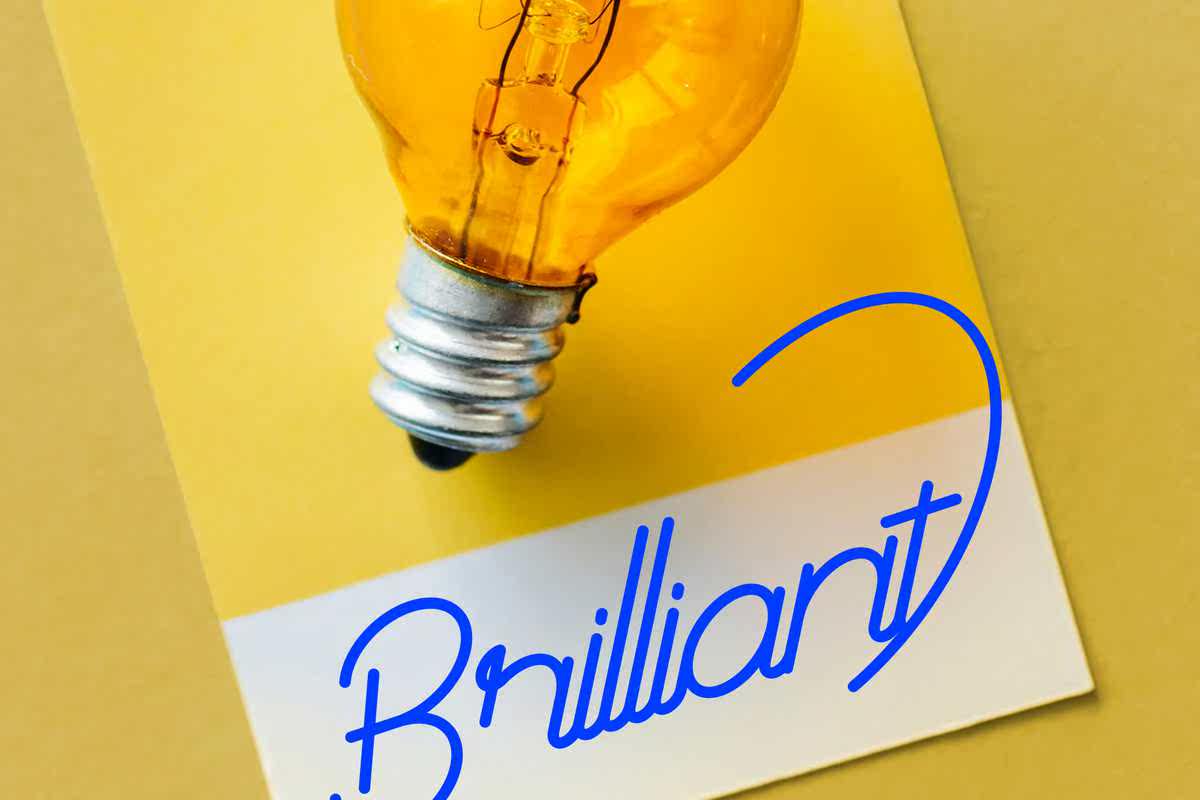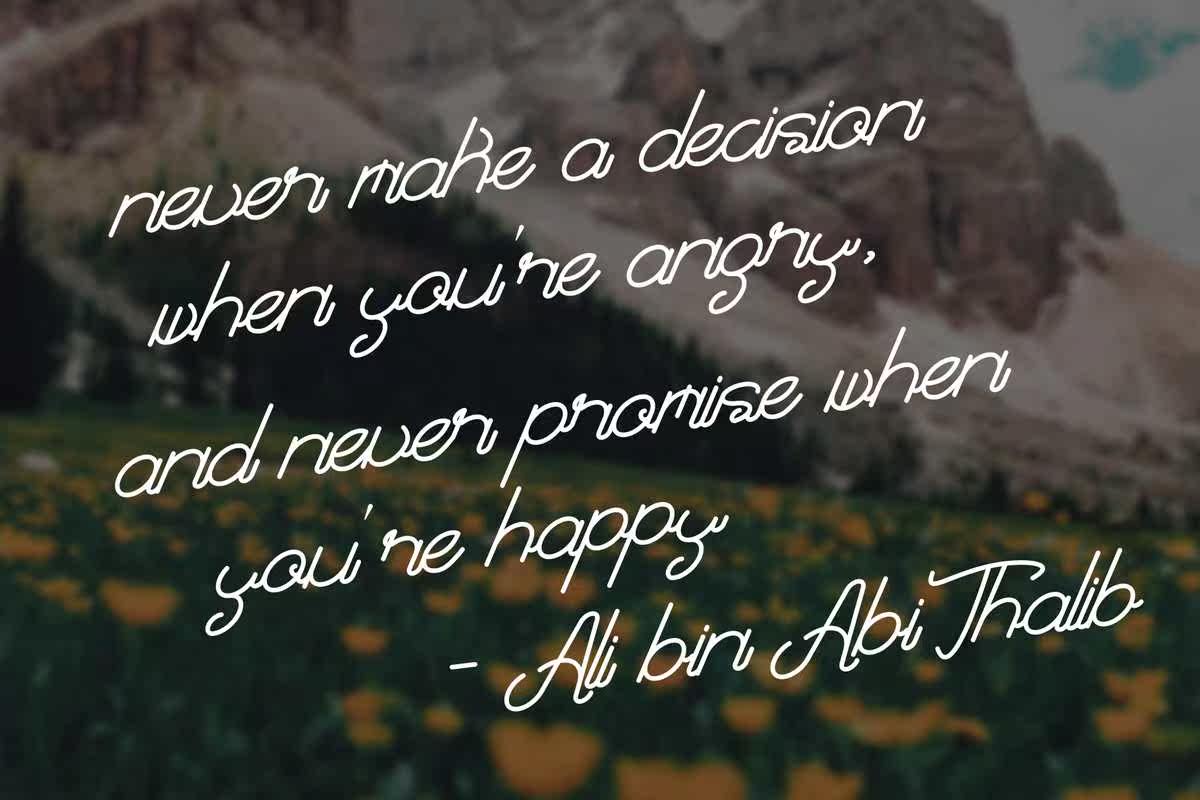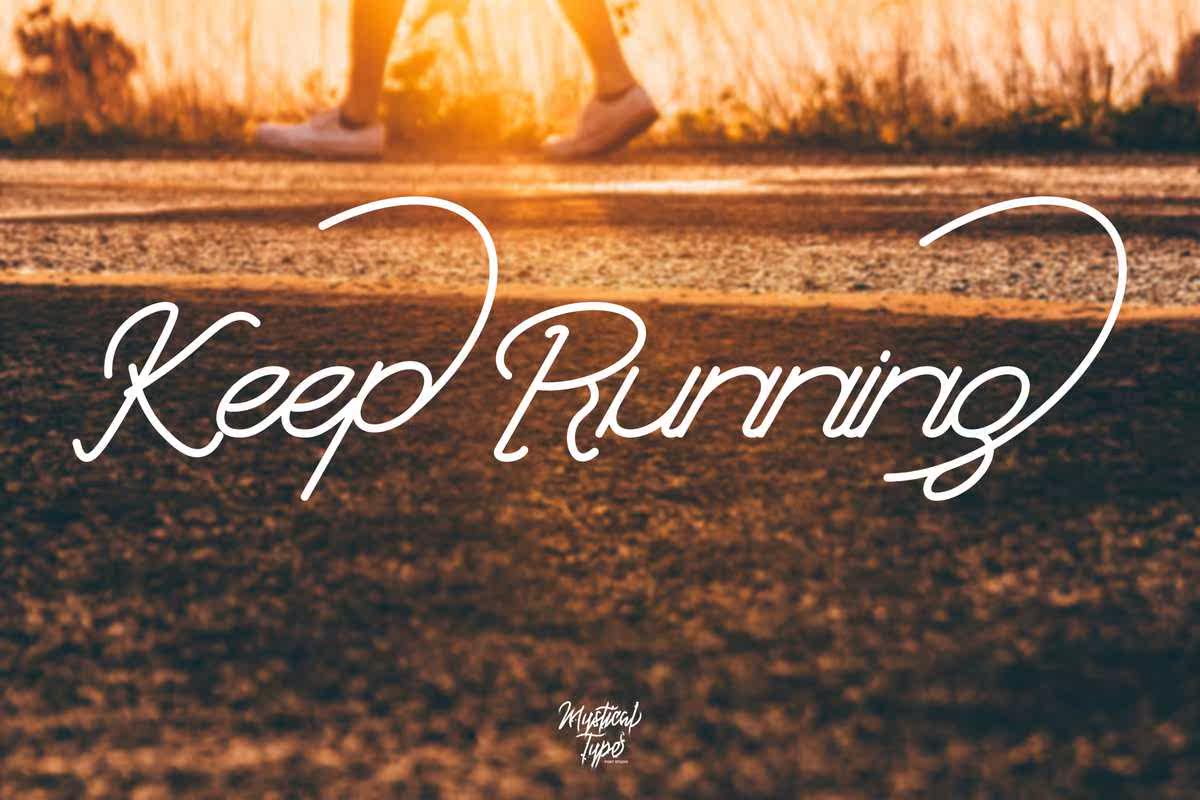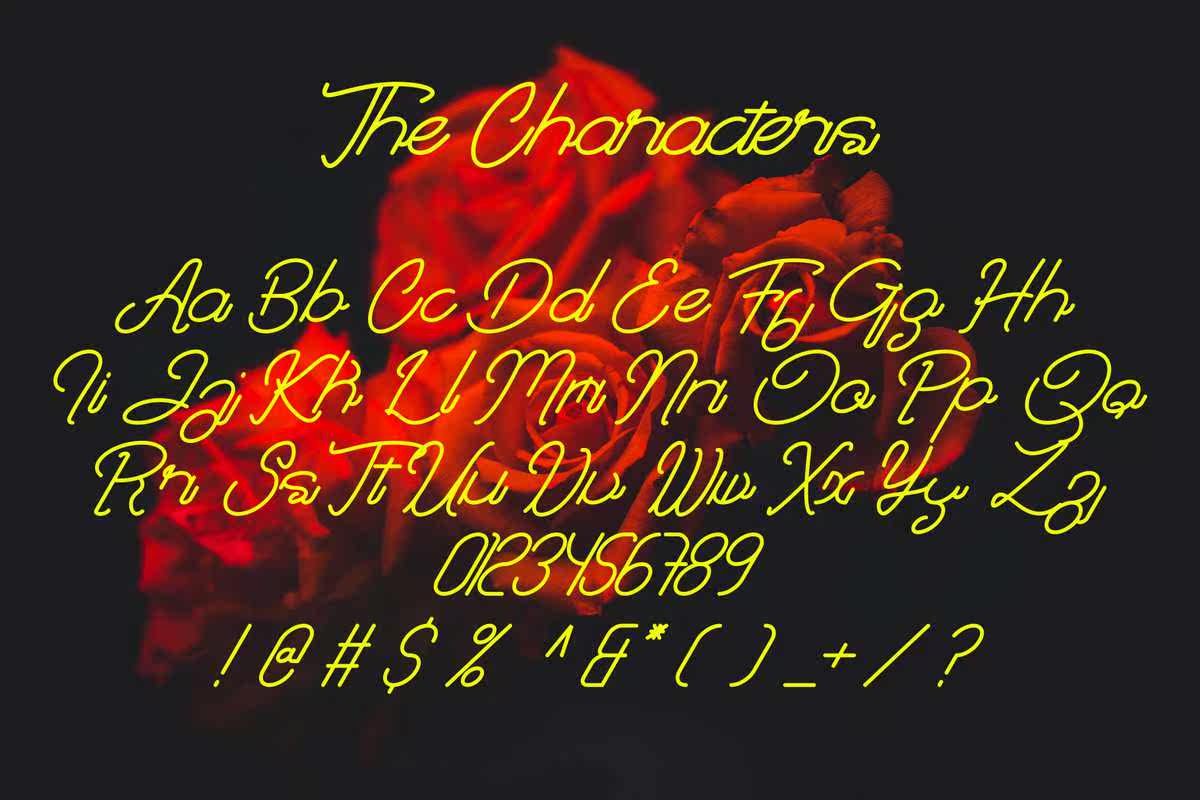
在为发射工作后,KhairaMonoline最终将被释放。KhairaMonoline是一种浓密的Monofont类型。它不需要将这种类型的字体变成一个项目。这是一种新的工具,您可以在许多人喜欢的页面中赋予您一个查看和写入权限。为发射工作后,KhairaMonoline最终已经发布。KhairaMonoline是一个很厚的单字体类型。它不需要在项目中使用这种类型的字体。这是一个新工具,您不想让您在许多人喜欢的内容中使用它。